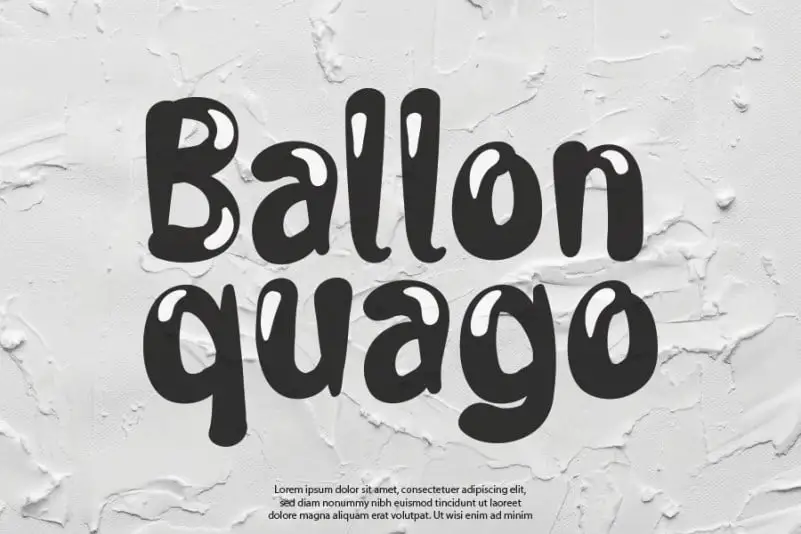
Ballon Quago Display Font – Download Grátis
A Ballon Quago Display Font é uma fonte display que traz uma rara mistura de bold e originalidade única. Suas formas leves e agradáveis ao olhar tornam esta fonte extremamente versátil, adequando-se a vários contextos. Essa característica faz dela um complemento ideal para qualquer design, seja ele simples ou elaborado. É perfeitamente adaptável a cartazes de loja, selos de marca ou até mesmo à capa de um livro de arte, sem deixar nada ao acaso. Adotando esta fonte em seu próximo projeto, você pode ser surpreendido por sua capacidade de criar designs excepcionais. A Ballon Quago Display Font é mais do que uma escolha gráfica; ela é a chave para dar vida e unidade a qualquer conjunto visual. Adquira-a agora para transformar suas criações em verdadeiros marcos da arte digital.